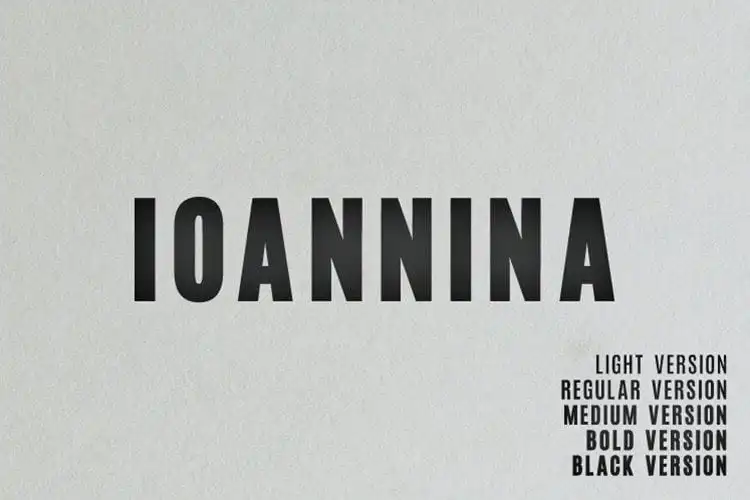
A Ioannina Sans Serif é uma elegante fonte geométrica de sans-serif que transmite sofisticação e universalidade com sua forma laconica e retangular. Ela foi criada por Shanaya, um designer-fontes talentoso. A Ioannina Sans Serif brilha em logos, cabeçalhos para sites web e materiais impressos, oferecendo uma aparência magnífica. Este pacote vem com quatro pesos (Light, Regular, Medium e Bold) além de uma versão Black Version. É perfeitamente adaptável para um amplo espectro de usos, desde a criação de logotipos memoráveis até os cabeçalhos profissionais dos sites da web e materiais impressos criativos. Seja você um designer gráfico ou editor, a Ioannina Sans Serif é uma escolha brilhante para suas próximas iniciativas de design.